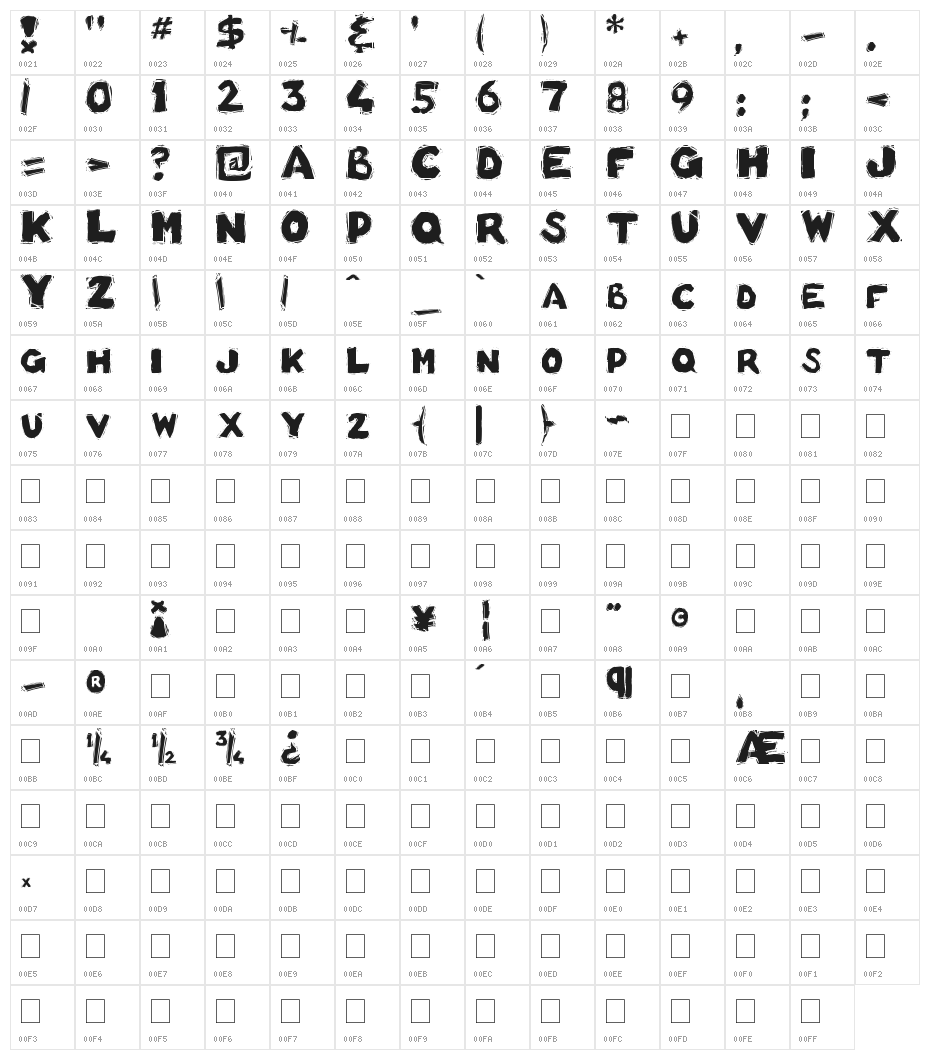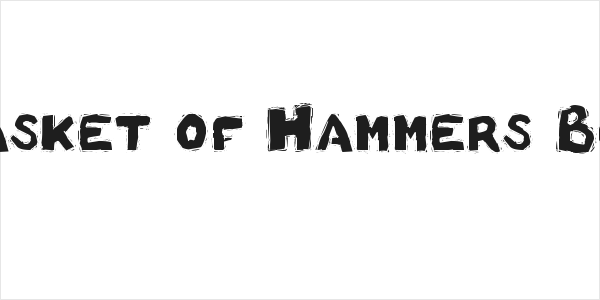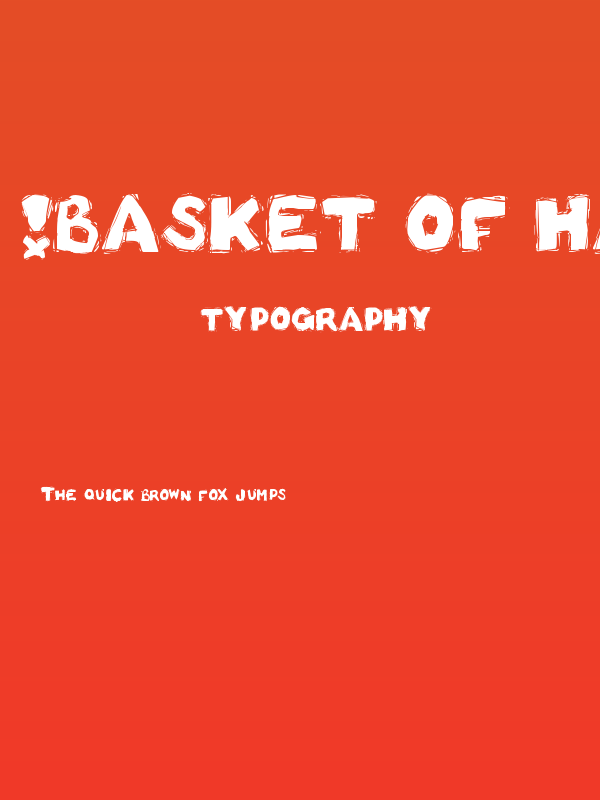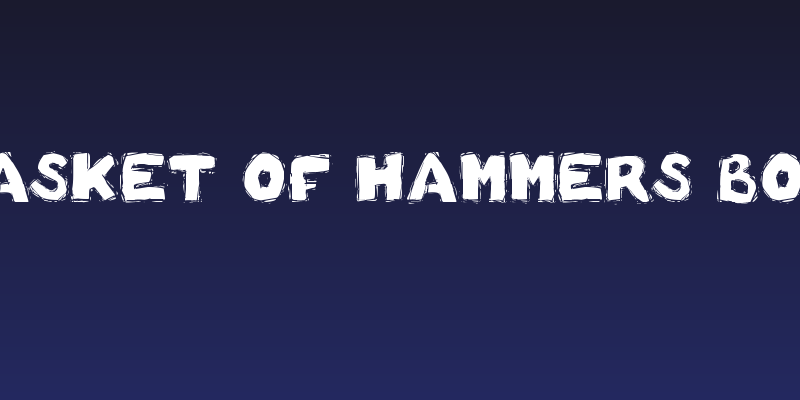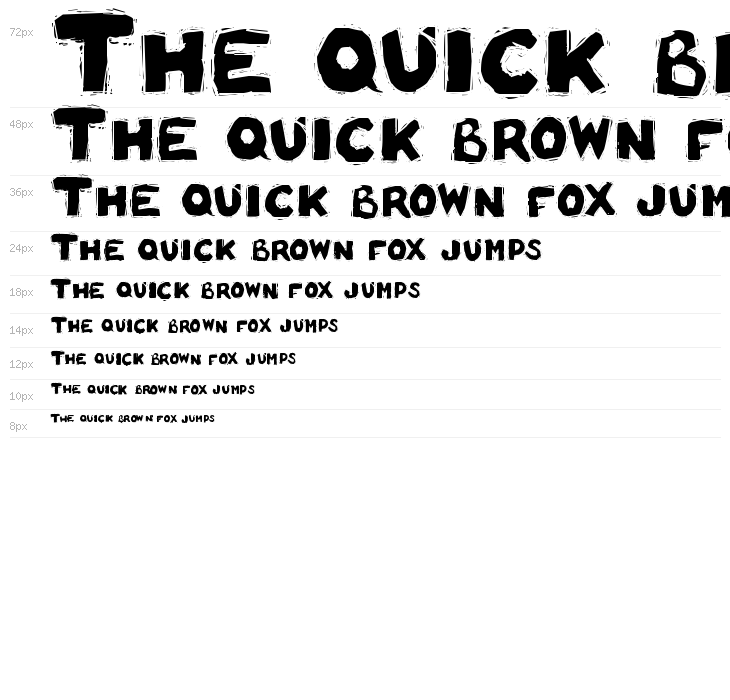
!Basket of Hammers Bold Font
| Общий стиль | Grunge, Urban, Edgy |
| Рекомендуемые проекты | Perfect for posters, album covers, streetwear branding, and any design needing a bold, edgy look. |